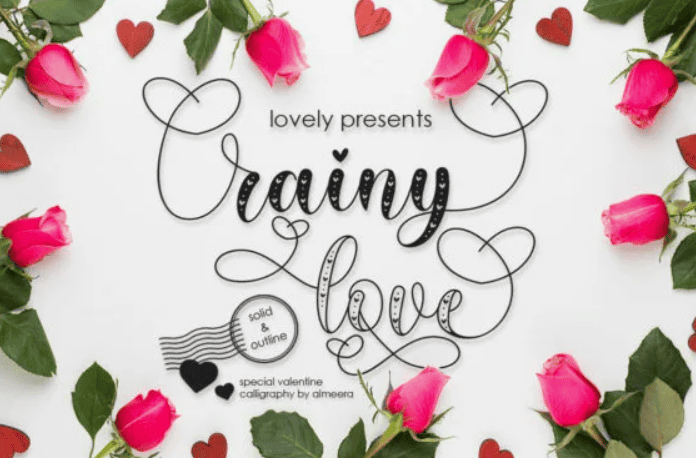
Название: Rainy Love Font
Rainy - это красивый рукописный шрифт с романтической тематикой. Влюбитесь в его невероятно универсальный стиль и используйте его для создания великолепных свадебных приглашений, красивого стационарного искусства, привлекательных постов в социальных сетях и многого другого!